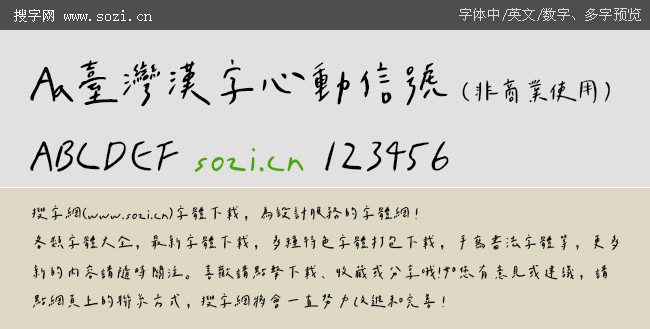
Aa臺灣漢字心動信號
搜字網(wǎng)給大家提供一款A(yù)a臺灣漢字心動信號(非商業(yè)使用)中文字體下載,該字體是一款手寫字體,字體筆觸纖細,字形流暢正,隨性灑脫,具有很好的視覺感,適用于平面宣傳設(shè)計、網(wǎng)頁設(shè)計、海報設(shè)計等應(yīng)用(此字體為個人非商用版,商用可以聯(lián)系QQ:1006760504)。